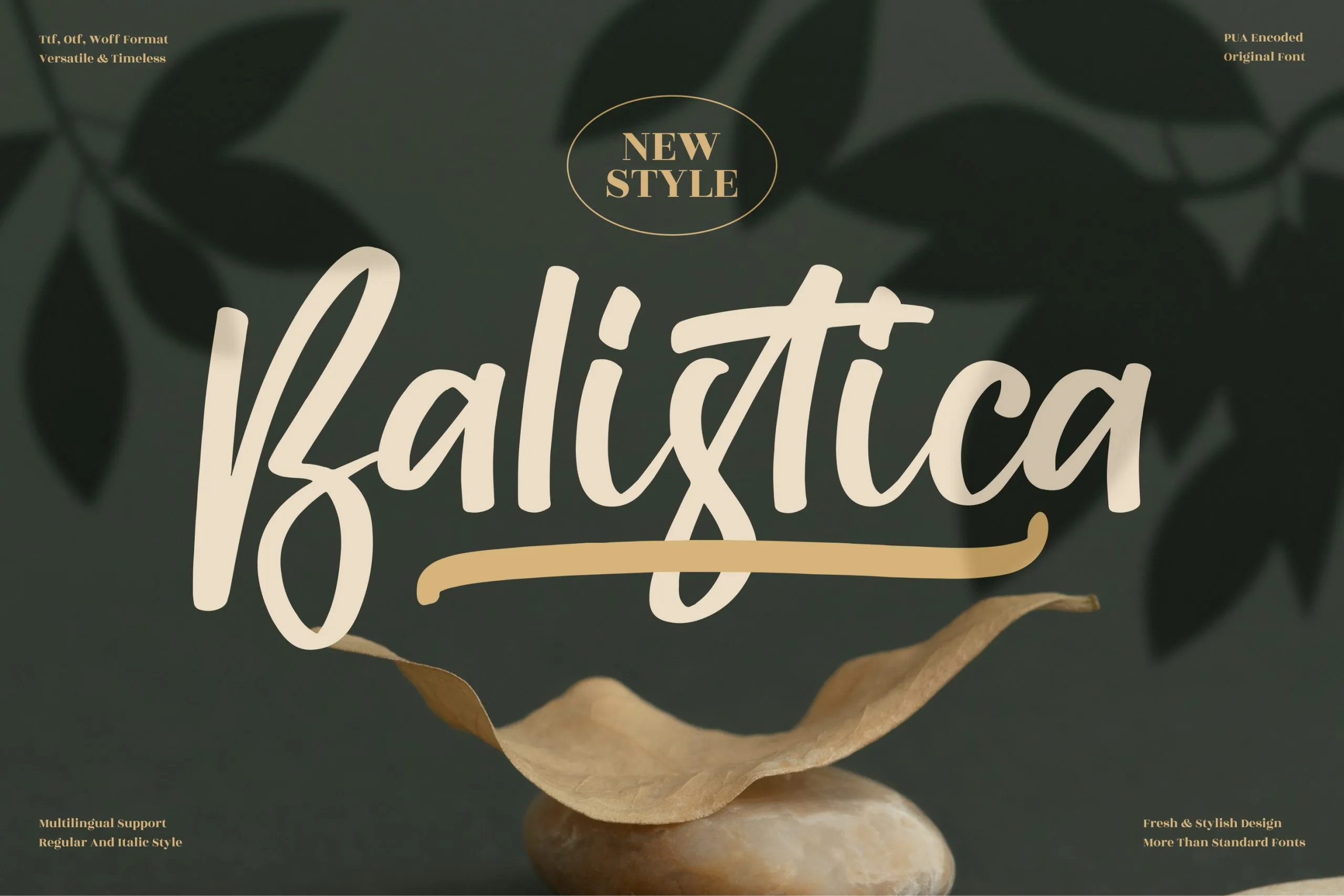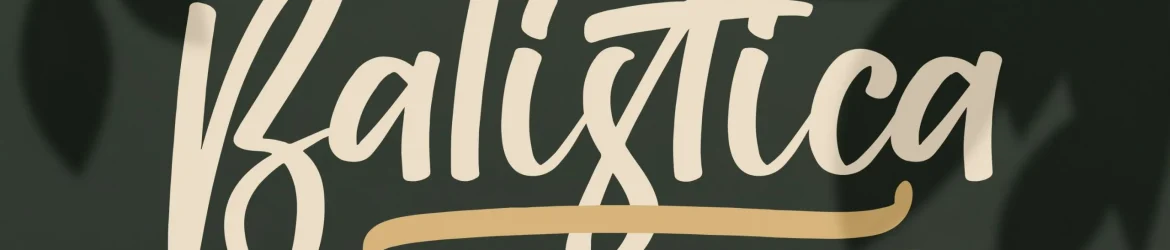
A fonte ‘Balistica Font’ é uma elegante assinatura para projetos premium, perfeita tanto para logos e campanhas de branding quanto para designs interiores, embalagens de produtos, mugs personalizados, cartazes publicitários, sacolas de compras, cartões de nome ou convites. Seu estilo autêntico permite que você personalize seu projeto, conferindo um toque sofisticado e único à sua criação. Para quem busca uma fonte elegante que brinca com o charme da escrita manuscrita, a ‘Balistica Font’ é definitivamente uma opção ideal. Com seus traços fluidos e nuances únicas, ela pode ser facilmente adaptada para qualquer projeto, garantindo um resultado impecável em sua próxima tarefa gráfica. A fonte ‘Balistica Font’, criada pelo designer perspectype, oferece o toque final perfeito ao seu trabalho de design.